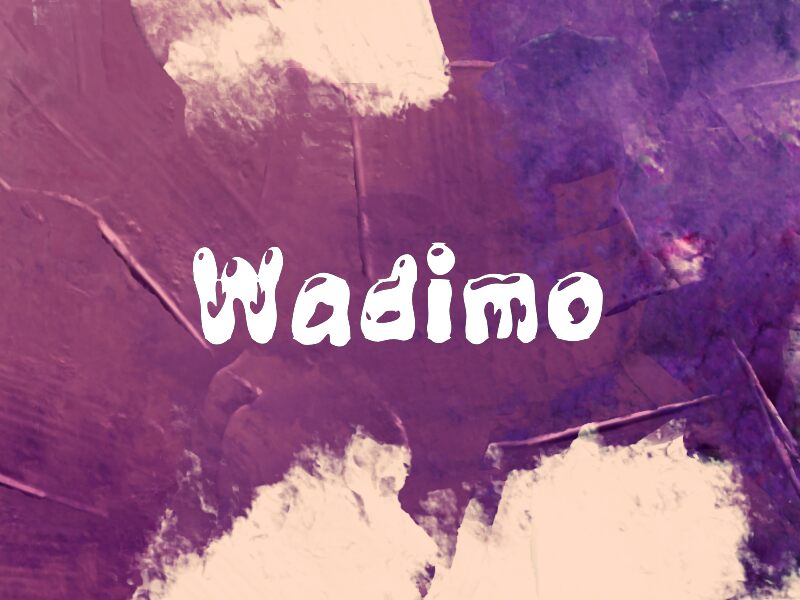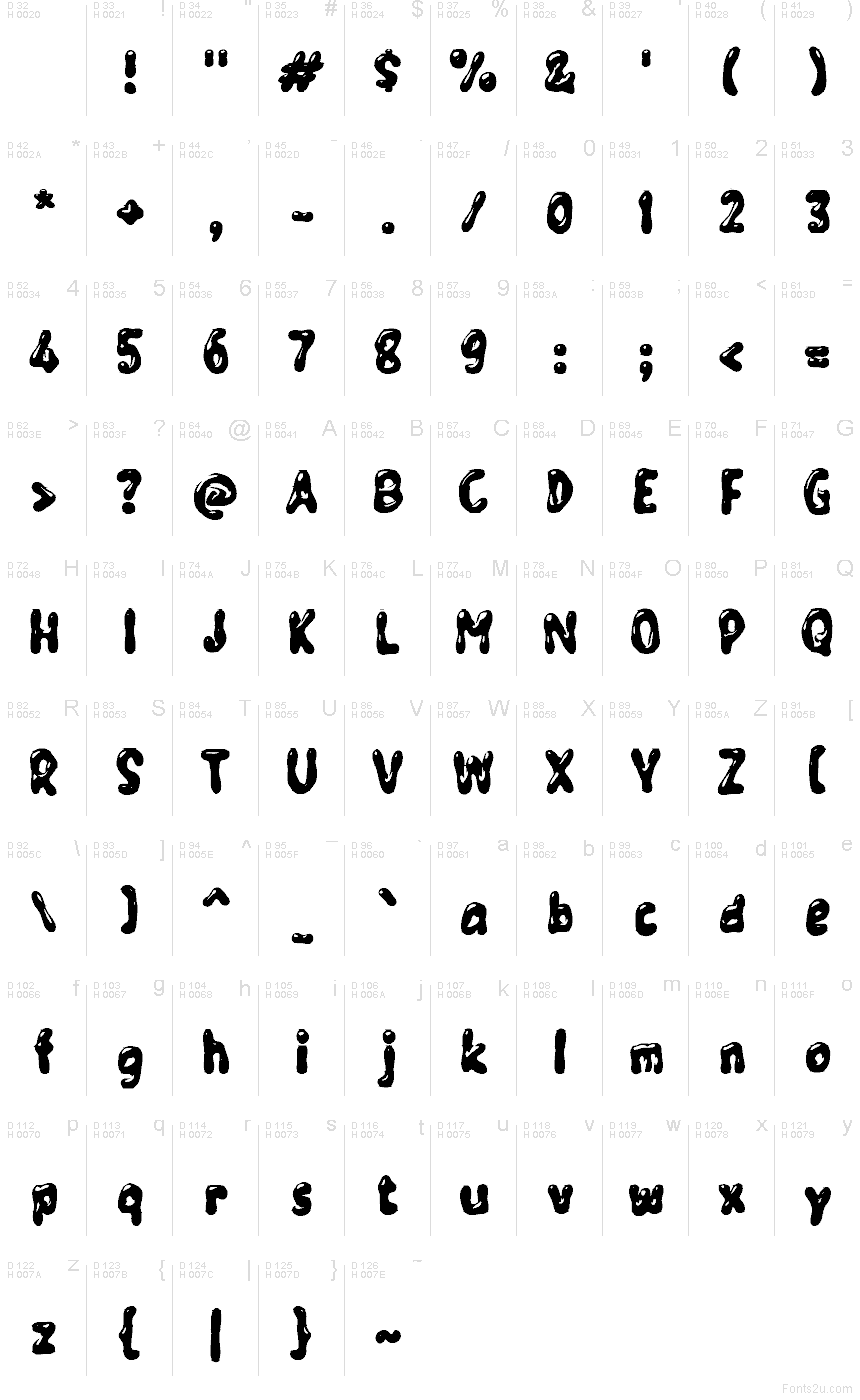
Wadimo
Wadimo от Wep - это бесплатный мультяшный акцидентный шрифт, напоминающий раздутые чернильные кляксы. Глянцевые белые вырезы придают буквам влажный и «резиновый» вид, а не просто скругленную форму. Эта повторяющаяся блестящая текстура придает дизайну тягучее, комиксное настроение и выделяет его на фоне стандартных игровых шрифтов.
Он идеально подойдет для приглашений на детские праздники, постеров в стиле слаймов, обложек для YouTube, упаковки снеков и заголовков комиксов, где мягкий силуэт кляксы становится частью истории. Шрифт лучше всего раскрывается в коротких заголовках, текстовых логотипах и графике для мерча, где объемные формы и блики создают эффект за счет массы и текстуры, а не за счет острых деталей.